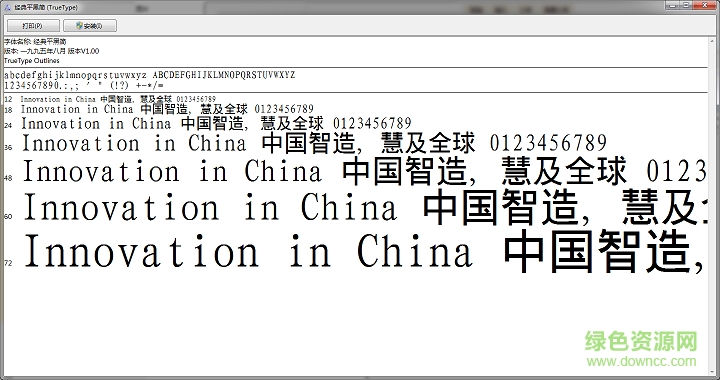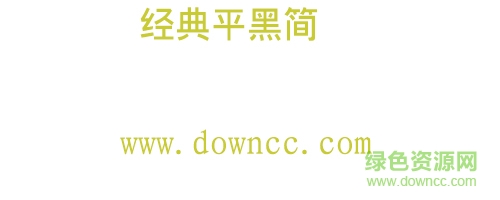
經(jīng)典平黑簡字體是一款筆畫非常規(guī)則的中文黑體字。該字體所有筆畫粗細一樣,非常勻稱,適用于廣告設計、印刷等行業(yè)。實用智能能讓你的廣告設計不斷的增加光彩,喜歡就來綠色資源網(wǎng)下載吧!
使設計方面的簡體中文字體,該字體端正大方得體,字形粗壯有力,整體效果非常出色,并且字庫完整,可以適用于名片設計、平面設計、廣告設計、報紙雜志等領域,有喜歡的網(wǎng)友可免費下載收藏